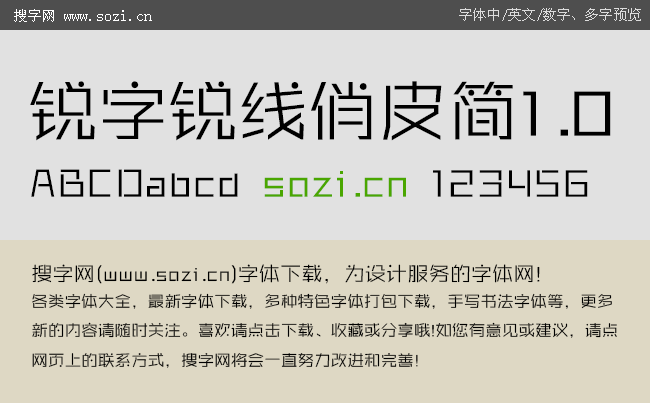
銳字銳線(xiàn)俏皮簡(jiǎn)1.0
搜字網(wǎng)提供一款銳字銳線(xiàn)俏皮簡(jiǎn)1.0中文字體下載,銳字銳線(xiàn)俏皮簡(jiǎn)是一款卡通風(fēng)格的中文藝術(shù)字體,該字體大方得體,俏皮可愛(ài),且字體完整,整體效果非常出眾,適合應(yīng)用于廣告設(shè)計(jì)、名片設(shè)計(jì)、包裝印刷、產(chǎn)品設(shè)計(jì)等應(yīng)用。
- 風(fēng)格類(lèi)別: 卡通字體